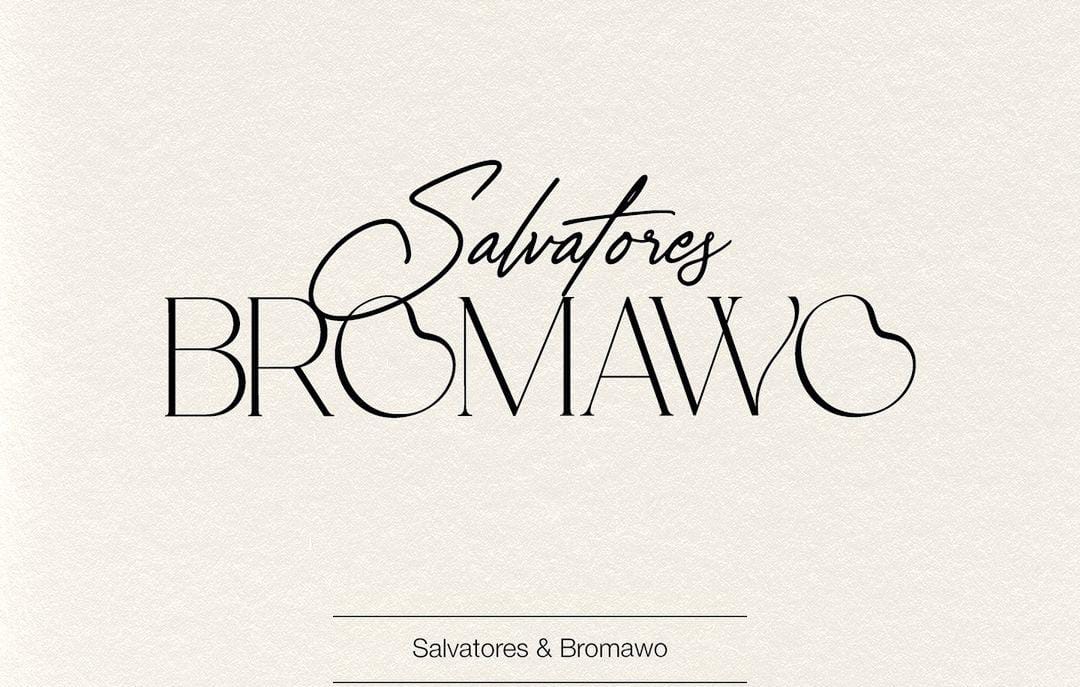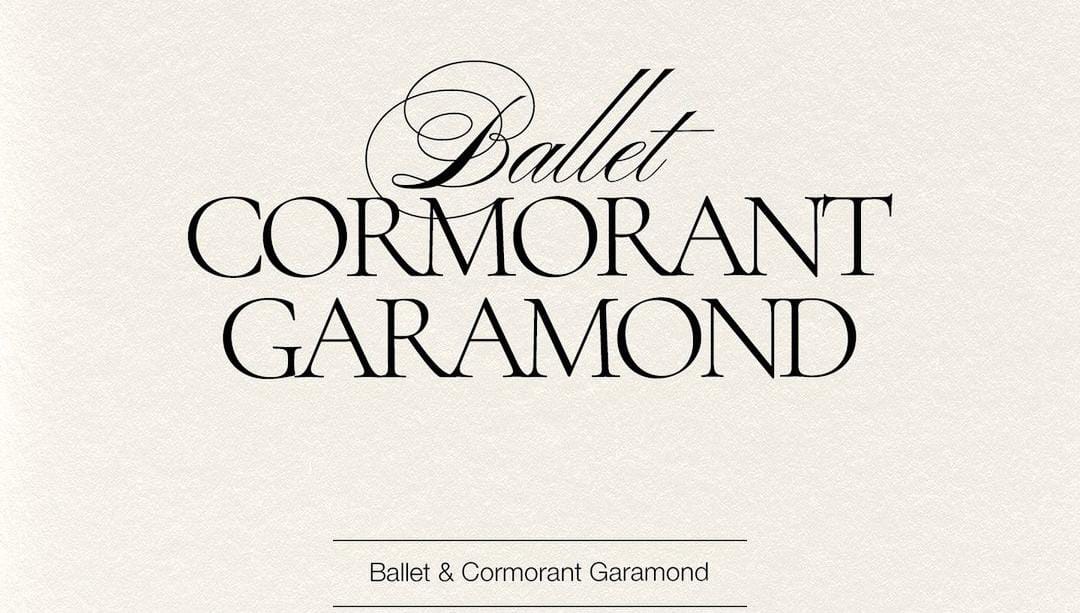
Kombinasi Font Elegan Kontras yang Sesuai Jenis Brand
Ketika ingin menciptakan kombinasi font yang kontras tetapi tetap sederhana dan sesuai dengan jenis brand, kombinasikan font yang harmonis. Dua jenis font berbeda dengan style yang mirip akan tampil harmonis serta kontras. Kombinasi dua jenis font elegan bisa menciptakan kontras jika mengatur ukuran, gaya huruf, dan ketebalan font.
Jenis font yang cukup kontras ini akan terlihat dari bentuk huruf dan gaya penulisan huruf, seperti script dengan gaya tulisan tangan akan kontras dengan font bersih seperti sans serif. Kombinasi gaya huruf yang kontras akan menciptakan tampilan desain brand menarik dan bisa menonjolkan informasi penting. Utamanya untuk membedakan font judul dan paragraf atau sub judul pada desain konten, poster hingga logo.
KOMBINASI FONT ELEGAN DAN KONTRAS SESUAI JENIS BRAND
Kombinasi font biasanya mengutamakan kemampuan dua font agar harmonis, selain itu penting untuk memastikan font tampil beda. Jika font yang dikombinasikan terlalu mirip akan kurang kontras dan kurang menarik. Berikut beberapa rekomendasi font elegan yang digunakan sesuai jenis brand seperti:
Font Ballet dan Cormorant Garamond
Dua font yang kontras tersebut menciptakan kombinasi yang harmonis dan menciptakan tampak sederhana. Meski menggunakan font elegan, kedua terlihat kontras karena dari dua jenis font yang berbeda. Kombinasi font script dan sans serif terlihat kontras, termasuk berkat penggunaan ukuran yang berbeda.
Gaya huruf script yang tipis dan elegan tampil kontras berkat dikombinasikan dengan font serif yang juga elegan. Kombinasi dua font menciptakan tampilan elegan dan minimalis cocok untuk digunakan dalam desain brand fashion. Untuk desain konten atau desain logo, kombinasi akan tampil menarik.
Font Playfair dan Hanken Grotesk
Kombinasi dua font agar kontras selain menggunakan jenis font berbeda, bedakan variasi ketebalan huruf sehingga menarik. Kombinasi font serif dan sans serif tersebut tampil sederhana dan minimalis, untuk menciptakan kontras atur variasi ketebalan huruf. Perbedaan ketebalan huruf pada font Playfair dan Hanken menciptakan kontras yang menarik.
Font Playfair yang lebih tebal akan digunakan sebagai font judul, sementara font Hanken untuk sub judul dan teks paragraf. Kombinasi yang cukup kontras ini bisa digunakan untuk jenis desain konten brand skincare. Font yang tebal akan memastikan judul konten mudah terbaca dan gaya font elegan mencerminkan karakter bisnis skincare dengan baik.
Font Salvatores dan Bromawo
Sesama gaya font yang tipis, penggunaan jenis font dengan gaya berbeda akan menciptakan kontras sekaligus kesan yang harmonis. Font script memiliki gaya huruf tipis dan memiliki gaya tulisan tangan yang alami. Font bromawo yang bersih dan memiliki garis huruf elegan membuat kombinasi dengan font script sangat harmonis.
Meski beberapa huruf dalam font bromawo tampil melengkung tetapi tidak mengurangi keterbacaan teks. Kombinasi font elegan yang kontras dapat dikombinasikan sesuai brand yang ingin memiliki citra elegan dan mewah. Penggunaan kombinasi font tersebut cocok untuk jenis brand jewelry dan fashion dress yang elegan.
Font Aftersick dan Corinthiago
Dua font yang memiliki jenis font berbeda serta gaya huruf yang kontras dapat tampil sederhana dengan kombinasi dua font sederhana. Font serif Aftersick memiliki sentuhan gaya huruf modern yang unik dan trendy. Gaya huruf yang cukup tebal membantu teks judul bisa kontras dari sub judul yang menggunakan font script tipis.
Kedua font tampil kontras, harmonis dan bergaya elegan, kombinasi font ini bisa membuat desain brand menonjol. Kombinasi ini dapat digunakan untuk jenis brand fashion, kecantikan hingga brand elegan lainnya. Pada desain poster penggunaan font yang tebal dan sederhana akan mencolok.
Brown Casalowa dan Great Day
Kombinasi font elegan yang kontras menggunakan font serif dan script cukup populer karena kontras tetapi juga harmonis. Pada kombinasi kali ini font serif yang digunakan sebagai font judul dengan huruf kapital. Gaya huruf yang tipis akan sulit membuat teks menonjol sehingga perlu menggunakan ukuran besar.
Sebagai font sub judul, gaya font script yang tipis dan bersih menciptakan tampilan yang menarik. Kontras antara font serif yang berukuran besar dan font script yang sederhana ini sering ditemui dalam jenis brand kecantikan. Kombinasi font kontras yang elegan ini sesuai untuk jenis brand kecantikan, fashion atau brand elegan lainnya, untuk berbagai jenis desain kombinasi font bisa membuat desain lebih menarik.
TIPS MENCIPTAKAN KONTRAS DALAM KOMBINASI FONT
Kombinasi font dalam desain brand harus sesuai identitas merek sehingga tampil relevan dan efektif. Kombinasi dua font yang kontras akan menciptakan desain yang menarik serta mampu meningkatkan keterbacaan teks. Dua gaya font berbeda bisa akan kontras jika menggunakan jenis font berbeda, ketebalan huruf berbeda serta ukuran teks yang berbeda.